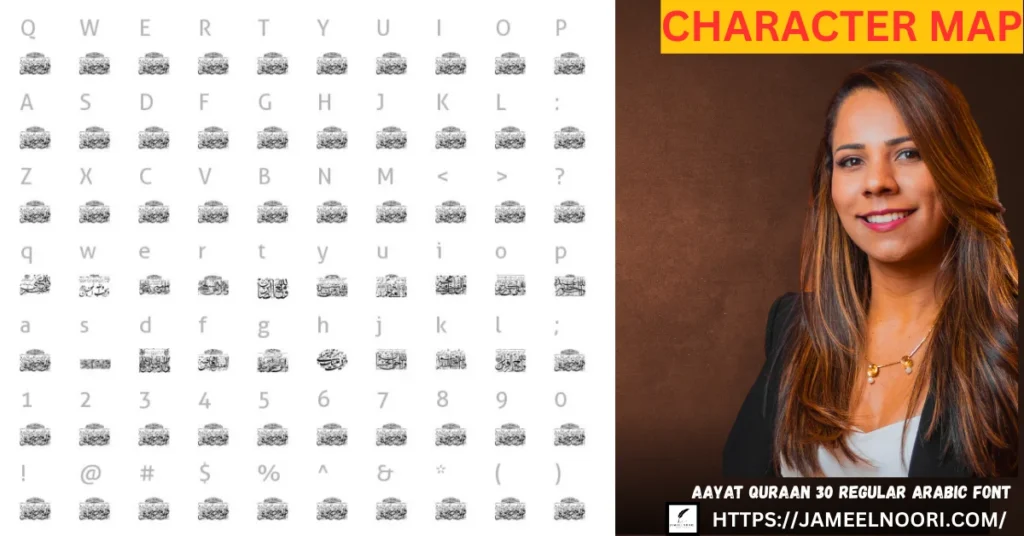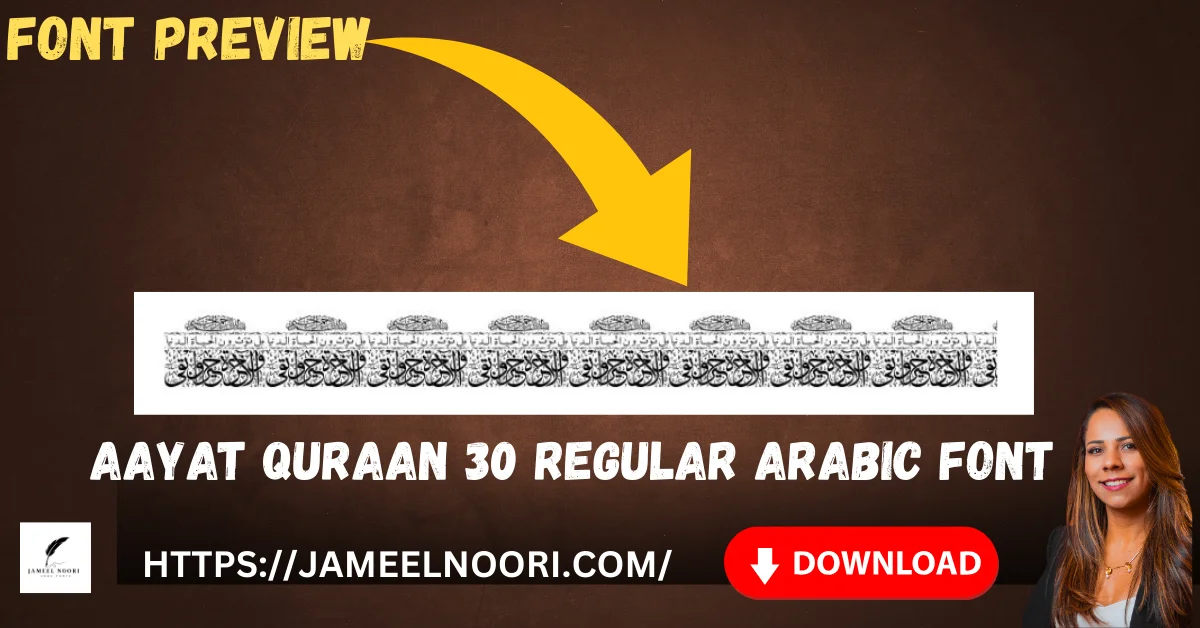
Aayat Quraan 30 Regular Arabic Font Pakistan me digital designers aur Quranic text lovers ke liye ek bohot hi popular font hai. Ye Regular TrueType Font hai aur isay ab tak 37,458 downloads mil chuke hain, jabke 190 users ne isay 5.0/5 rating di hai. Is font ki khas baat iska unique calligraphy style hai jo Quranic text ko elegant aur readable banata hai.
Key Features of Aayat Quraan 30 Regular Arabic Font
| Calligraphy Style | Elegant Quranic Script |
Why Choose Aayat Quraan 30 Regular Arabic Font for Your Projects
Aayat Quraan 30 Regular TTF Arabic Font ko select karne ki bohot si wajahain hain. Ye font Quranic text aur Urdu typography ke liye specially design kiya gaya hai.
- Smooth Character Shapes: Har letter ki shape bohot refined aur smooth hai.
- High Readability: Quranic aur Urdu text me clarity aur elegance maintain hoti hai.
Best Uses of Aayat Quraan 30 Regular Arabic Font
Aayat Quraan 30 Regular Arabic Font ke kai applications hain:
- Digital Quran Projects: Quranic apps aur websites me text ki clarity ke liye.
- Graphic Designing: Urdu fonts aur Arabic fonts design projects me.
- Printing Projects: Invitations, banners, aur posters me.
Aayat Quraan 30 Regular vs Other Arabic Fonts
Analysis: Agar aapko Quranic aur Urdu typography me professional quality chahiye to Aayat Quraan 30 Regular Arabic Font sabse best choice hai.
Tips for Using Aayat Quraan 30 Regular Arabic Font Effectively
Conclusion: Make the Best Choice with Aayat Quraan 30 Regular Arabic Font
Agar aap Quranic text aur Urdu typography me best result chahte hain to Aayat Quraan 30 Regular Arabic Font aap ke liye perfect hai. Ye font smooth, elegant aur highly readable hai, aur download aur installation process bohot simple hai. Pakistan ke users ke liye ye ek professional aur SEO-friendly choice hai.
Is the font suitable for Quranic projects?
Yes, this font is specially designed for Quranic text.